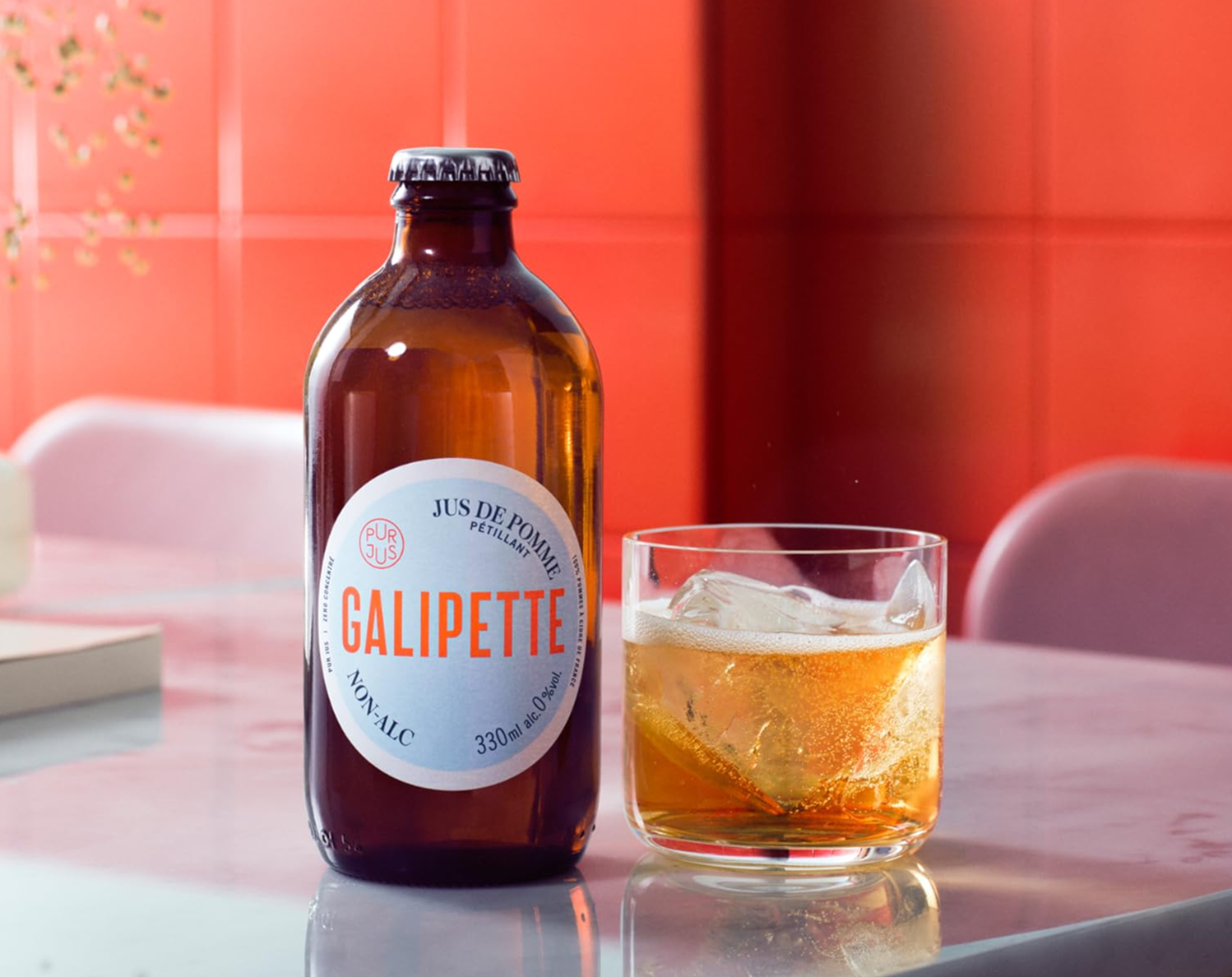
Galipette — сидр, который делают из яблок, выращенных на небольшой ферме во французской Бретани. На его этикете, сделанной в студии Werklig, за типографику отвечают Austin студии Commercial Type и Trade Gothic Linotype.
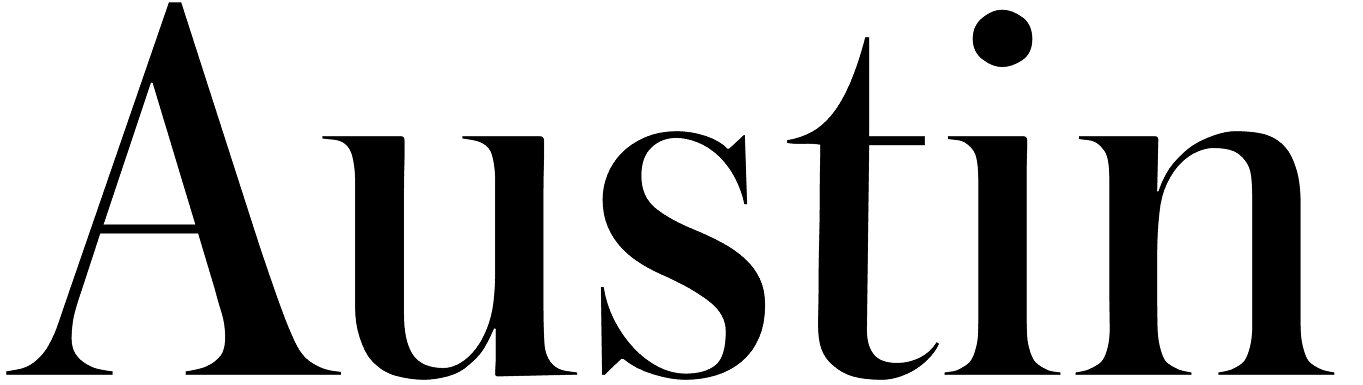
Austin — англо-шотландская антиква, нарисованная Полом Барнсом для издательского дома Hearst Magazines. Austin отсылает к работам пуансониста Ричарда Остина, но за счёт более узких знаков и более сильного контраста выглядит гораздо экспрессивнее прототипов. Кириллицу для Austin нарисовал Илья Рудерман.